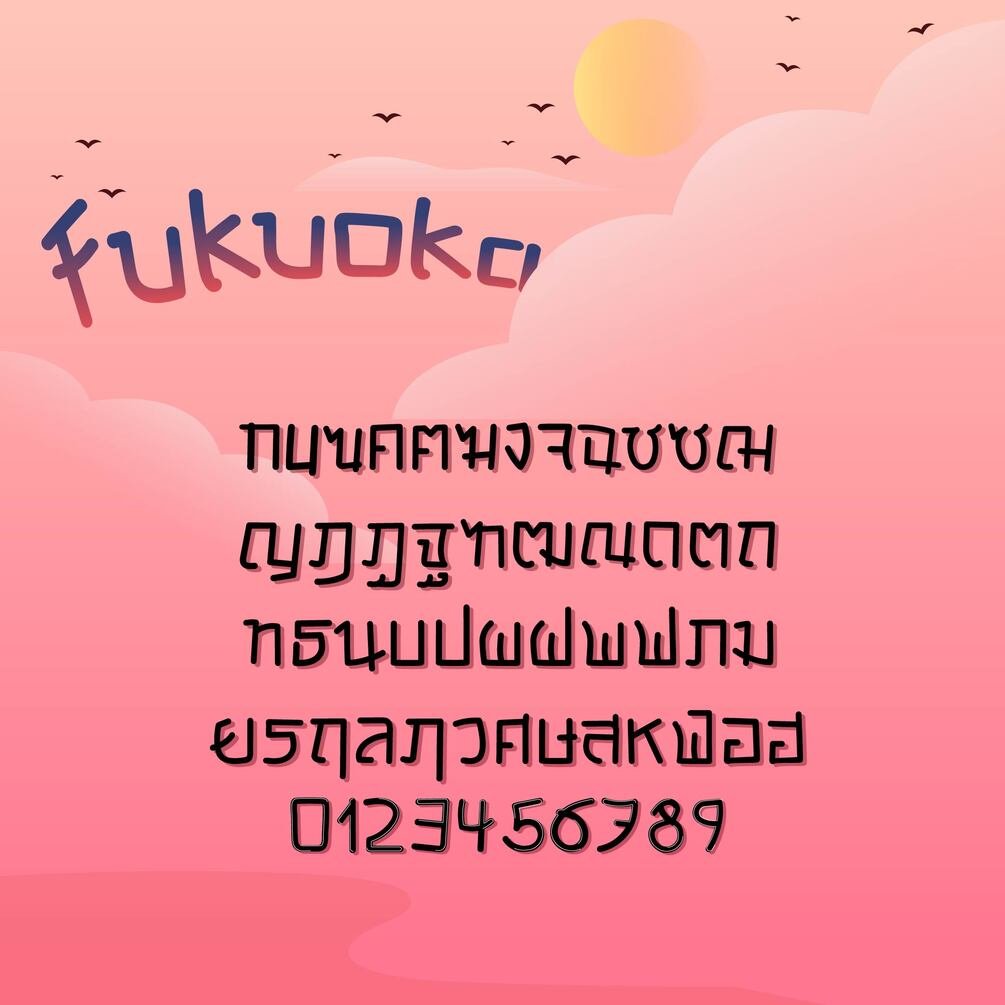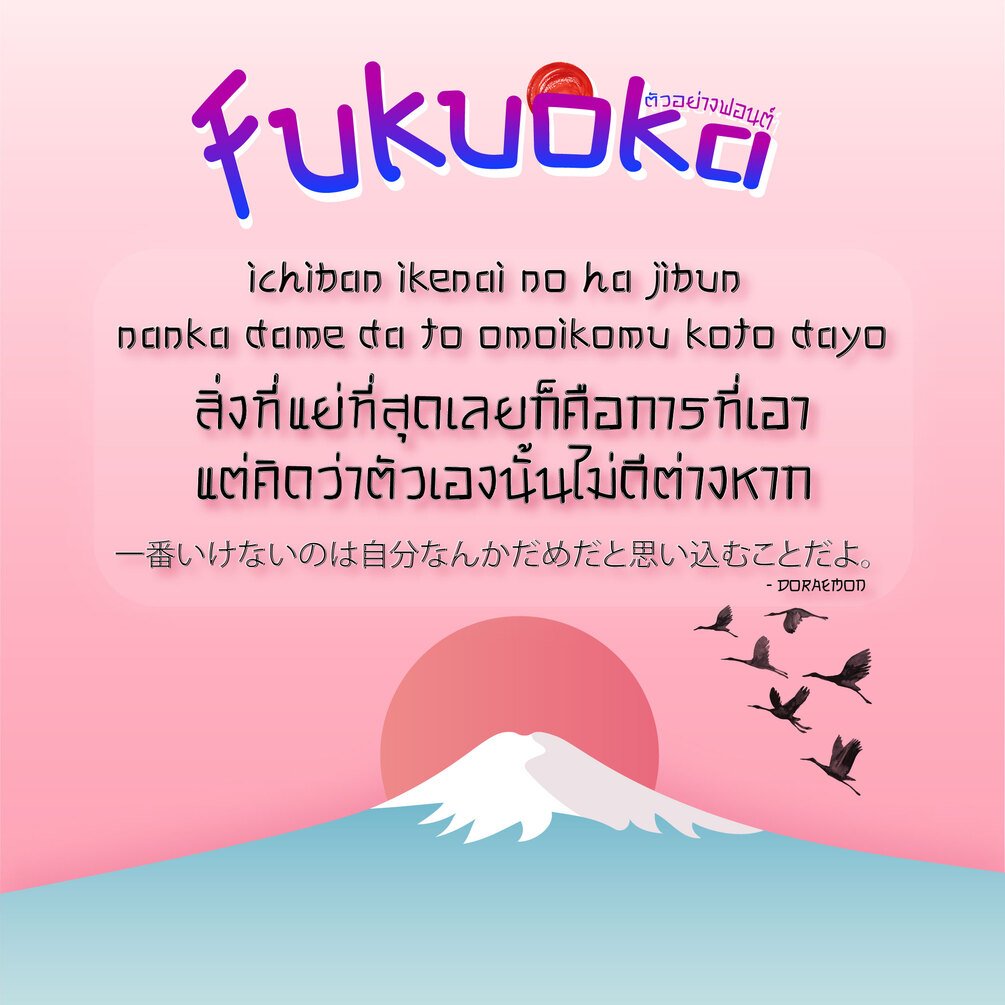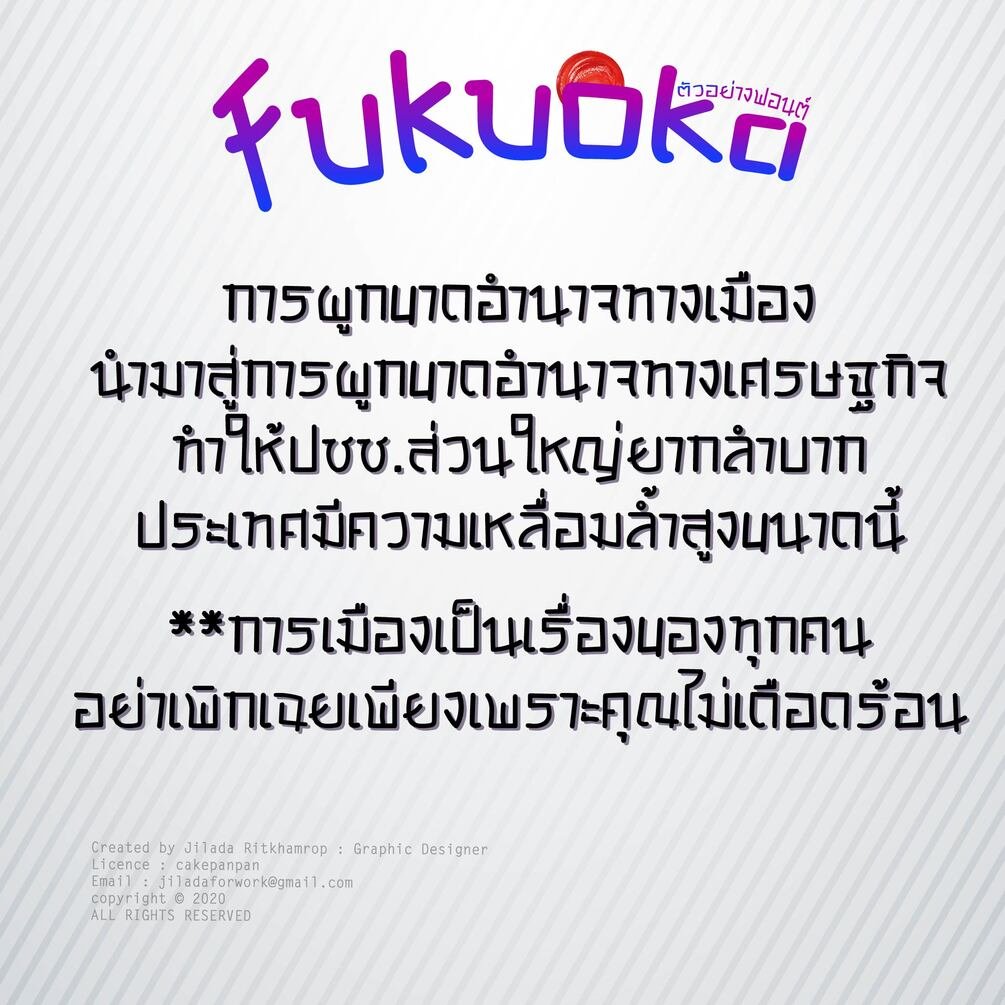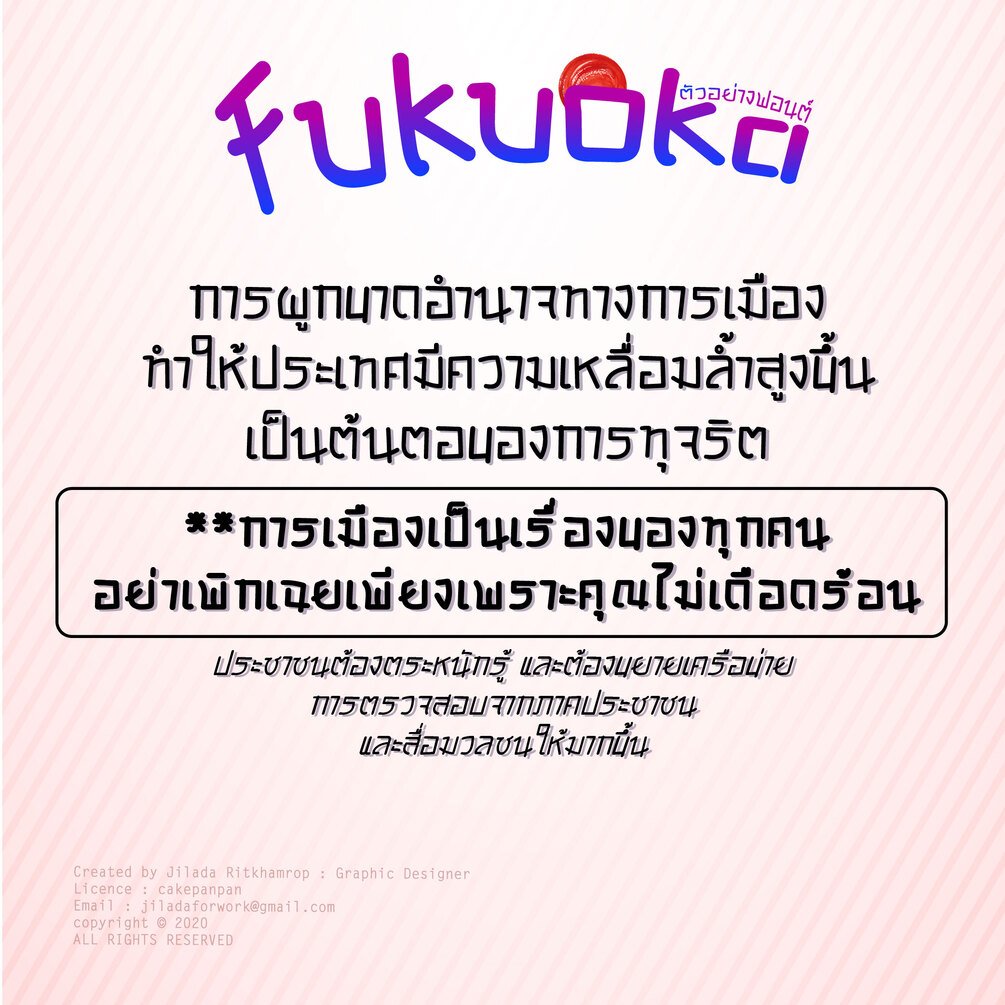
Fukuoka Font (ฟอนต์ฟุกุโอกะ)
ฟอนต์สไตล์ญี่ปุ่ง~ 🏯 มีทั้งภาษาไทยและภาษาอังกฤษเลยนะคะ มีตัวปกติ ตัวหนา และตัวเอียงค่ะ ฝากไว้ในอ้อมอกอ้อมใจพี่จ๋าด้วยนะจ๊ะ 🥰